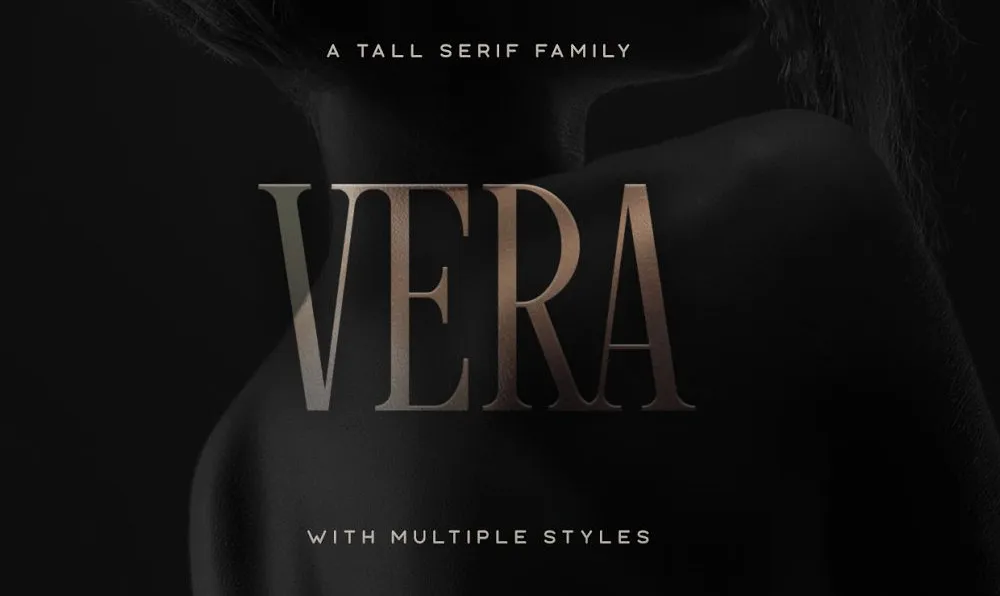
Vera Typeface é uma fonte serif de exibição altinha e estreita criada pelo Hamilton para uso em cabeçalhos elegantes nos espaços apertados, como convites, capas de revistas ou títulos. Introduzida pela Tugcu Design Co., Vera possui três diferentes estilos: suave, regular e cânico. Este font inclui caracteres maiúsculos em várias línguas, letras alternativas, números e pontuação. Suas linhas são alongadas e suas serifas levemente finas, tornando-a perfeita para usar em headlines sofisticadas e espaçadas com grande precisão, especialmente nas publicações de mídia que exigem um design minimalista e elegante. Sem dúvida, Vera Typeface é uma escolha ótima para aquelas aplicações que buscam equilíbrio entre beleza visual e utilidade funcional.